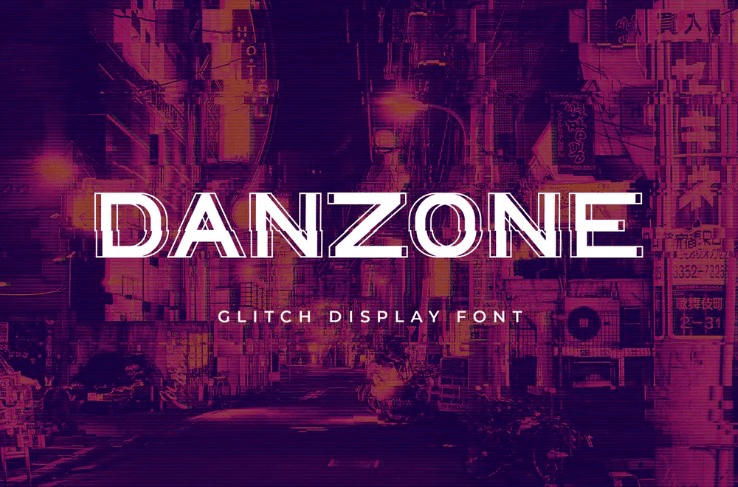
Danzone Sans Serif Display Font
Представляем наш новый продукт под названием Bright open Sans Serif Display Font с его уникальными шрифтами и насекомыми, что делает его одним из самых запоминающихся шрифтов заглавных букв на рынке. Этот шрифт идеально подходит для модного брендинга или редакционного дизайна и отображает как мужские, так и женские качества. Вы также можете использовать этот шрифт в дизайне логотипов и этикеток, дизайне одежды, музыке, рекламе, футболках, брошюрах и многом другом!